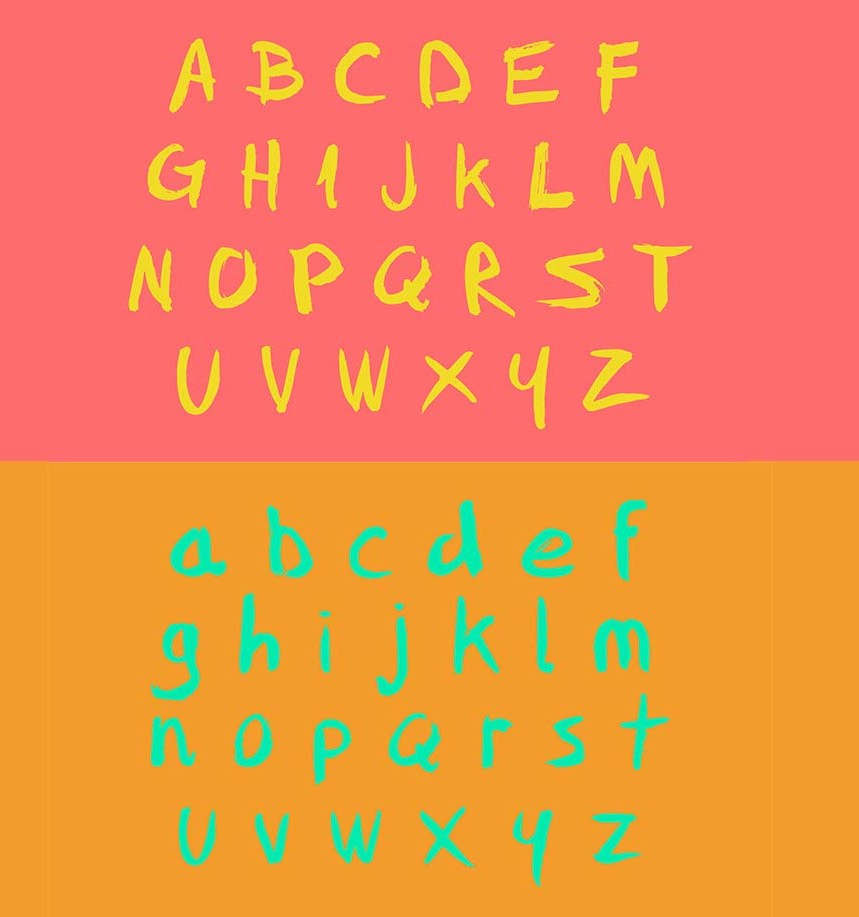
La monday font de hoy se trata de FFAD Matro una fuente de letra manuscrita con ligaduras y con algunos caracteres especiales para conseguir esa sensación más real. Gratis para uso personal y comercial, gracias a SuperBruut. El enlace de descarga está disponible abajo.